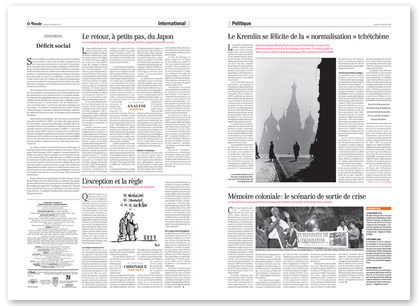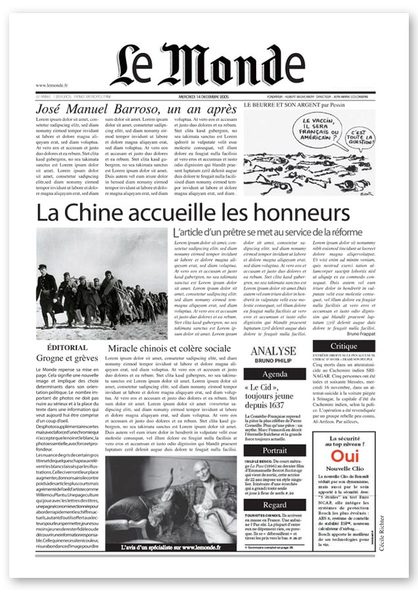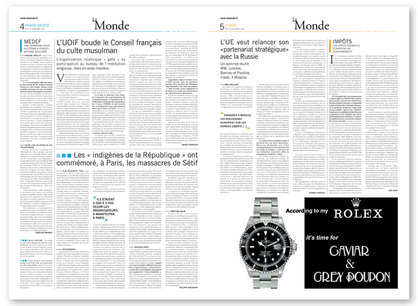
Le Monde vu par les élèves d’une école de communication visuelle
C’est donc naturellement, après avoir présenté mes analyses de la nouvelle formule du journal que j’ai donné à mes élèves d’e-art sup, le soin de réfléchir à une nouvelle maquette qui tiendrait compte de mes conclusions présentées tout au long des notes précédentes.
En résumé, Le Monde, grand journal quotidien de tradition républicaine draine un lectorat exigeant tant sur les contenus éditoriaux que sur la forme graphique. Universitaires, chercheurs, étudiants, cadres et fonctionnaires (à majorité l’éducation nationale), constituent le cœur de cible du journal. Un lectorat cultivé, diplômé, habitué aux couloirs des écoles et facultés, habitués donc à la recherche de l’information et d’une approche individuelle de la synthèse. Pour toutes ces raisons ce lectorat ne ressent pas, au contraire, les mêmes besoins d’hiérarchisation de l’information que celui d’un Parisien libéré ou d’un France soir, voire d’un Metro ou d’un 20 minutes. Il préfère une couverture exhaustive de l’info qui lui permet de se forger tel Montaigne une idée personnelle de l’Histoire qui se déroule sous ses yeux. Les photos, bien sûr, nécessaires pour l’illustration de certains articles ne constituent pas non plus la trame d’une lecture qui se veut «de fond». Nous avons convenus avec mes élèves d’un traitement de l’image noire et blanc pour revenir aux fondements du photojournalisme, permettant à la fois une expression contemporaine de l’actualité en gardant ses distances avec l’anecdotique image couleur qui éloigne le lecteur de l’essentiel, le Papier, l’Article.
Techniquement il y a beaucoup à redire sur ces maquettes, ils sont loin d’être parfaits. Manque de temps, obligation d’avancer dans un programme chargé, les élèves survolent le sujet et tentent de donner une réponse aussi personnelle que possible tout en respectant un brief très contraignant. L’outil informatique joue un rôle primordial dans l’élaboration d’un tel projet. Il permet de tester la grille, le gris typo, le rythme du journal, les logos etc.
Voici donc les maquettes les plus représentatives :
détails (cliquez pour agrandir)
maquettes de Matthieu Kobler [e-art sup]: un logo gothic simplifié, une mise en page plutôt minimaliste qui fait la part belle à un édito que personnellement je n’aurais pas composé sur deux col. mais cela se défend. L’éditing est sobre mais très lisible. Il manque bien sûr une structuration des articles (chapôs, intertitres etc.), mais dans l’ensemble une maquette plutôt élégante et exigeante.
maquettes de Julie Le Page [4e année, e-art sup]. Très professionnel, un sens journalistique très mur, on sent qu’elle a bien compris les enjeux d’une rédaction. Sommaire, articles, brèves, structure, éditing, photos, tout y est organisé pour que les journalistes puissent prendre en main leurs espaces d’écriture. Typographie élégante [Times PC eh oui + Myriad façon Frutiger], qualité d’une icono photojournalistique. J’ai été plutôt impressionné par cette maquette à la fois lisible et d’une texture très agréable, qui donne envie de lire un journal.
maquettes de Cécile Richter [e-art sup], qui a préféré rompre an douceur avec La tradition du Logo historique. Dommage qu’elle ai conçu sa maquette sur un format réduit 29,7 x 42, ça manque d’espace, de volume à bâtir. Mais j’aime assez l’esprit à la fois rigoureux et décalé, si l’on considère la gymnastique typographique de la double. La Une est sobre et permet à la fois la publication d’une double info majeure. Toutes ces maquettes sont assez respectueuses des contraintes journalistiques, même s’ils doivent être adaptées, corrigées, améliorées. [typographie: Times, Bauhaus, Myriad]
maquettes de Claire Tagliaferri [e-art sup]. C’est sans doute celle pour laquelle j’ai un faible. Logo imparfait, manque de puissance, mais j’aime bien l’idée de bousculer l’establishment. Par contre la structure typographique, la subtilité de la grille montée sur 5 col. avec une économie des moyens dans l’usage des filets verticaux (c’était une demande personnelle, préalable à toutes les maquettes, parce que j’étais parti du principe qu’un bon projet doit se tenir sans filets de séparation, on n’en rajoute que pour suggérer, ou lorsqu’il en va vraiment de la compréhension de l’articulation du journal). J’aime beaucoup cette irruption des codes graphiques «magazines» dans l’élaboration d’un quotidien. Le journal est lisible, rythmé, architecturé… prêt à être rubriqué. Et toujours un traitement noir et blanc de la photo qui lui redonne cette dimension qui manque complètement aux photos couleurs. En découvrant cette maquette j’ai pensé à Robert Delpire qui aimait allier la belle photo d’un André Kertész avec des typos lubaliniennes. Lisibilité et élégance.
Vous remarquerez aussi le remarquable travail sur les gris typos. je sais c’est mon DaDa, mais n’est-ce pas là la texture même du journal qui est en jeu. À quoi servirait de faire une belle maquette avec une typo mal réglée (cf. ma note sur le gris typo dans la rubrique lisibilité-visibilité). [typographie: Versailles et Trade Gothic]
maquettes de Pascal Vu Duc-Huy, que je trouve intéressant pour avoir installé d’abord une grille sur six col. puis un équilibre judicieux entre texte et photos (toujours noirs et blanc). Le journal est trop propre, entendez par là qu’on sent sinon l’amateurisme, un manque d’engagement journalistique. Là les rédacteurs devront se faire une place, revendiquer leur espace. Mais les choix d’un éditing sont là. Un Franklin Gothic ExtraCond et un New Aster ainsi que l’Optima et l’Eurostyle Bold qui viennent rythmer les enjeux d’une information sans cesse en mouvement. Cette maquette n’est sans doute pas finie. Les inters manquent. Les articles sont trop longs, il faudra restructurer. Mais là encore pas de filets. Et ce parti pris donne une grande élégance contemporaine à cette mise en page. Reste qu’il y a tout à reprendre, revoir et corriger. Sur de bonnes bases. C’est tout.
Ce programme a bénéficié de 12 heures de cours en classe et le reste au domicile des élèves.
Le sujet de ce rendu n’était qu’un prétexte (bien à propos) pour habituer les étudiants à découvrir et monter une grille de journal (jamais fait auparavant), à régler une qualité de composition, à évaluer des masses de textes en fonction d’un espace donné, à découvrir aussi la typographie, les conditions d’une lisibilité optimale, les valeurs d’emphase et d’élégance gutenbergiennes. Les quelques règles en usage. Mais aussi et surtout à mettre la typographie au service d’un message, d’une information, d’un produit. Le Monde n’en est pas un, on l’a déjà dit ici, mais il se fabrique selon des usages, des codes et des chartes de qualité. Et surtout avec une envie d’en découdre avec l’information! Ce travail ne peut-être jugé qu’à l’aune de conditions de réalisation identiques avec des étudiants-graphistes.
Ci-dessus la maquette de Claire Tagliaferri au format réel. Vaut la peine de la regarder en détail.